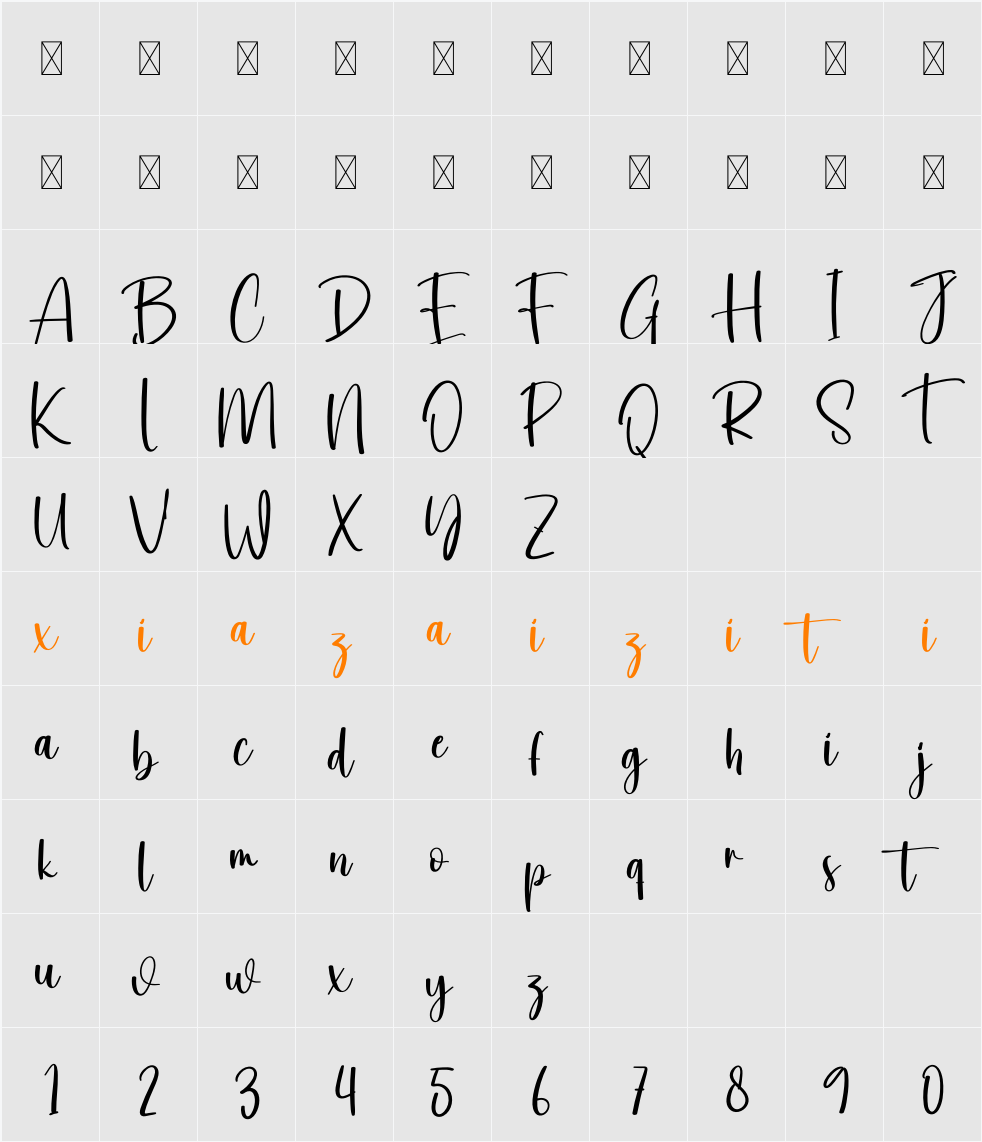
Winterlive
Winterlive,这款字体结构工整、笔画清晰,兼顾美观与易读性,适用于标题、正文、海报、包装、LOGO 等多种场景。字形优雅稳定,风格百搭耐看,适配日常排版与创意设计,让文字呈现更舒适、更具质感。Winterlive一笔一画,皆是细节,以均衡的比例、流畅的线条打造舒适视觉体验,字形端正大气,风格简约现代。无论是商业设计、品牌宣传还是日常排版,都能轻松驾驭,让文字更有格调与力量。Winterlive字体下载。